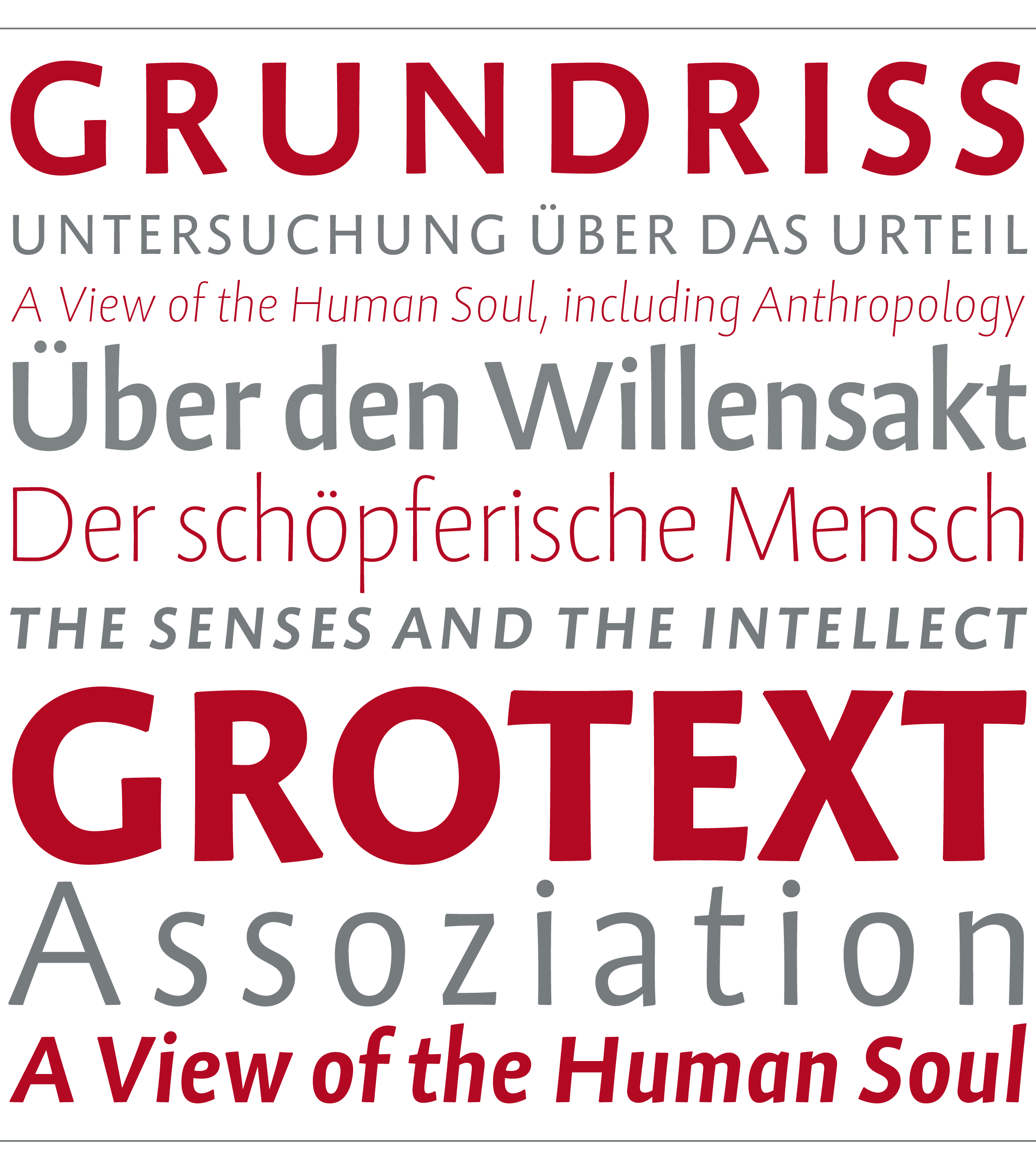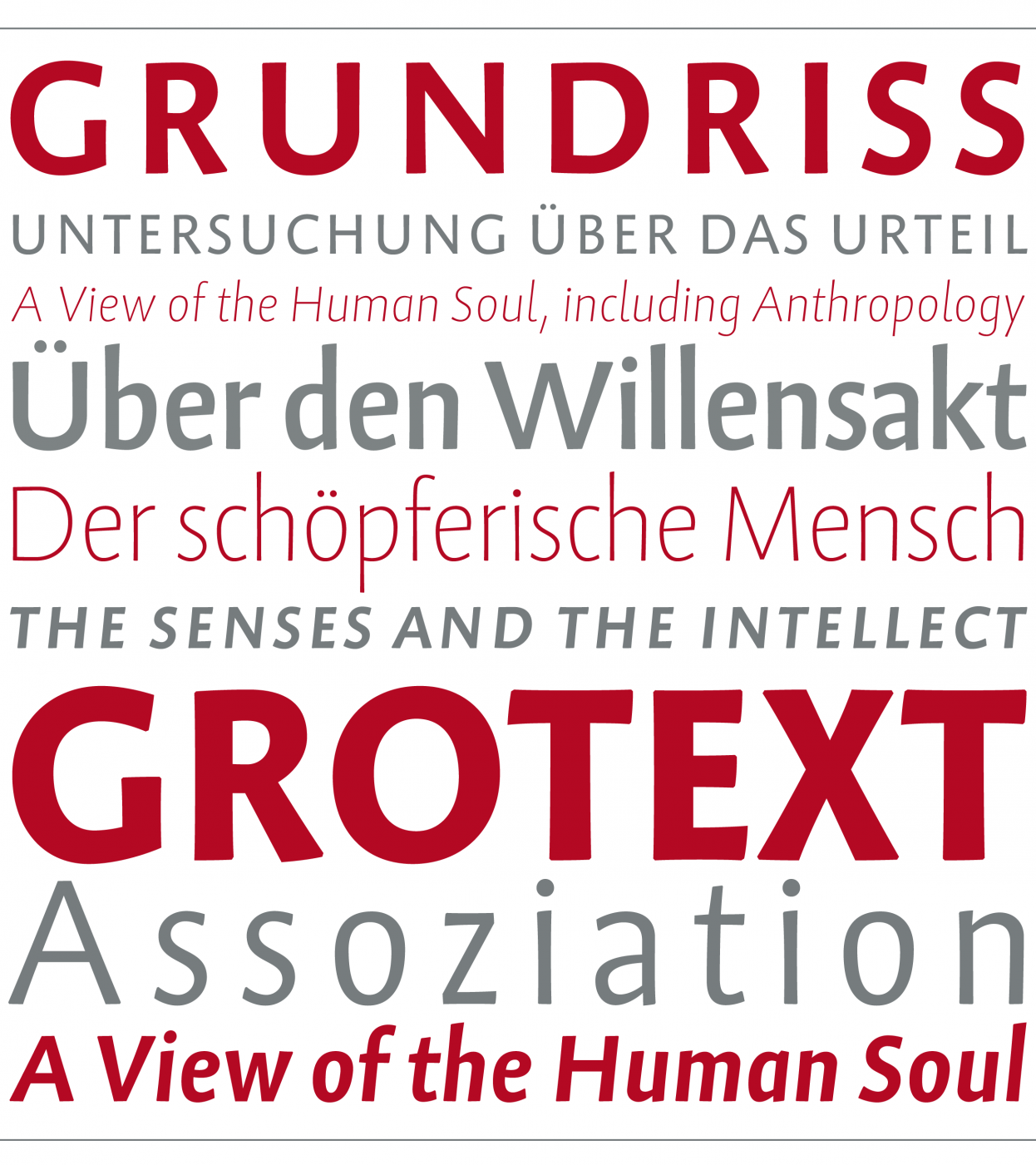
Erst gestern entdeckt: Fonts aus dem Hause KLTF gibt's seit November auch bei Fontspring - und zwar noch bis Jahresende zum günstigen Einstandspreis. Zum Beispiel die wunderschöne Grotext  (Manual (engl., PDF), Beispiele (engl., PDF)) für 122,50 statt regulär 350,00 US$ (Desktop-Lizenz für alle 14 Schnitte; die kleineren Pakete sind entsprechend reduziert). Da konnte ich einfach nicht widerstehen. Schon seit Monaten kann ich mich nicht an ihr sattsehen. Dabei habe ich nach wie vor keinen Plan, was ich überhaupt damit anfange  ... Hat oder findet jemand Beispiele, wo sie eingesetzt wird?
Latinotype Magnolia
Ich finde sie ja ganz hübsch – generell finde ich Latinotype recht ansprechend in letzter Zeit. Leider habe ich noch nicht gefunden wie lange das Angebot steht :-?
Den Ohrwurm schenke ich euch dazu :nicken::-)
Bei MyFonts endet das Sonderangebot am 27. April um 5:00 AM. So steht es zumindest in der Liste der Sonderangebote. Auf der Magnolia-Seite hißt es dann allerdings: This item is currently not for sale.